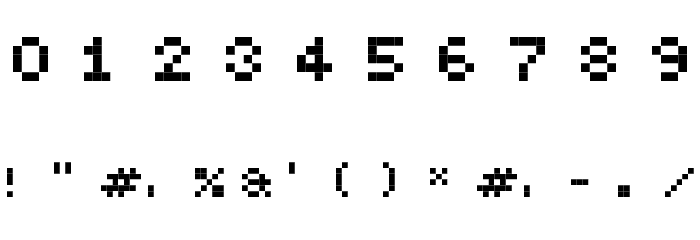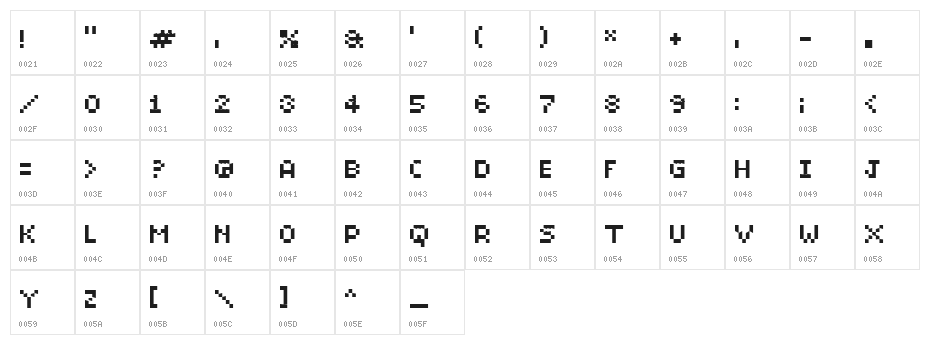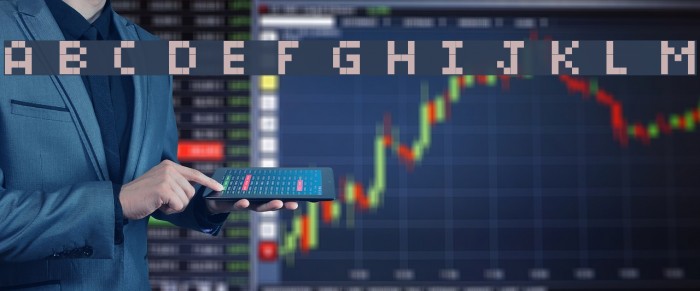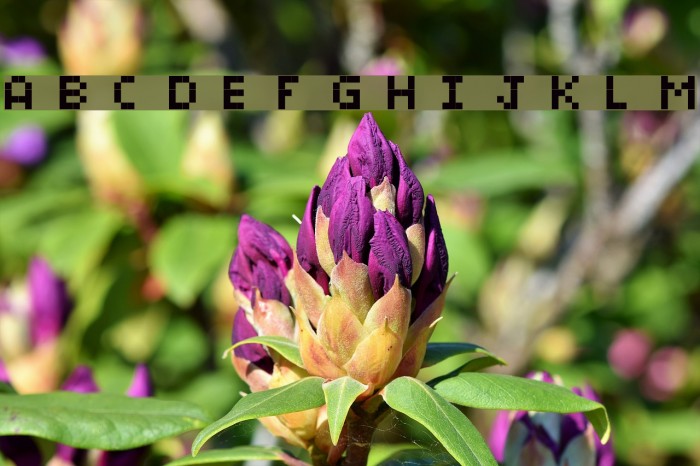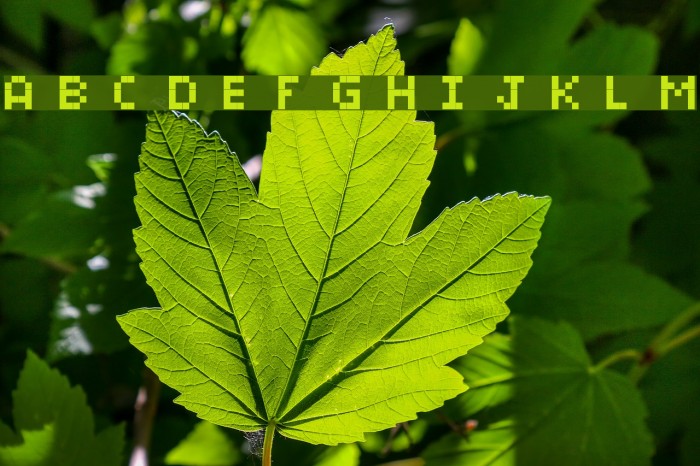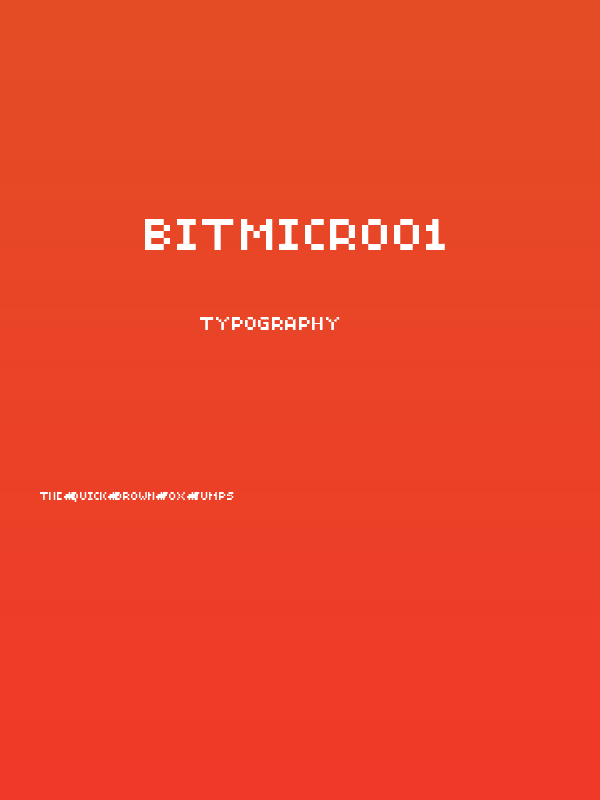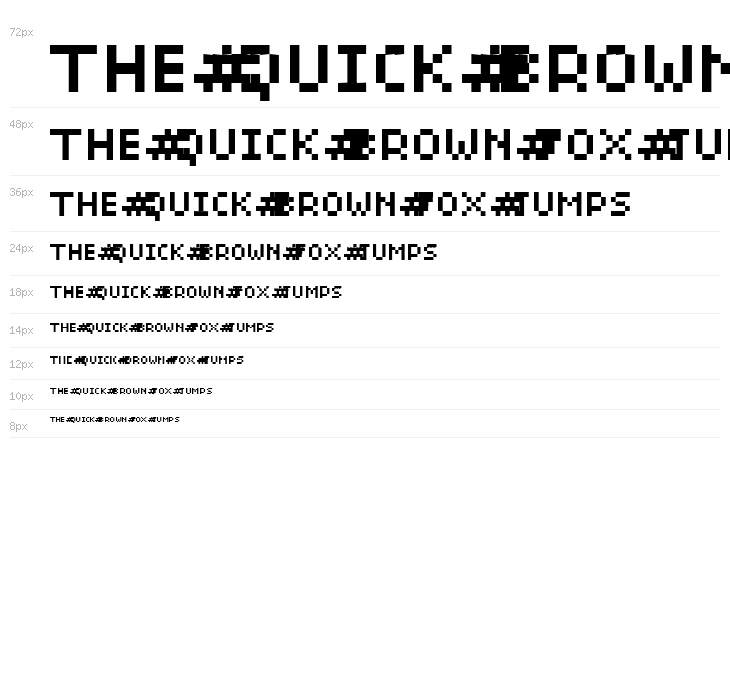
BitMicro01 Font
✎ Pixel
| 用途 | Logos, Digital displays, Coding interfaces |
| おすすめプロジェクト | Perfect for retro video game designs, digital art projects, coding interfaces, and any creative work that requires a nostalgic digital feel. |